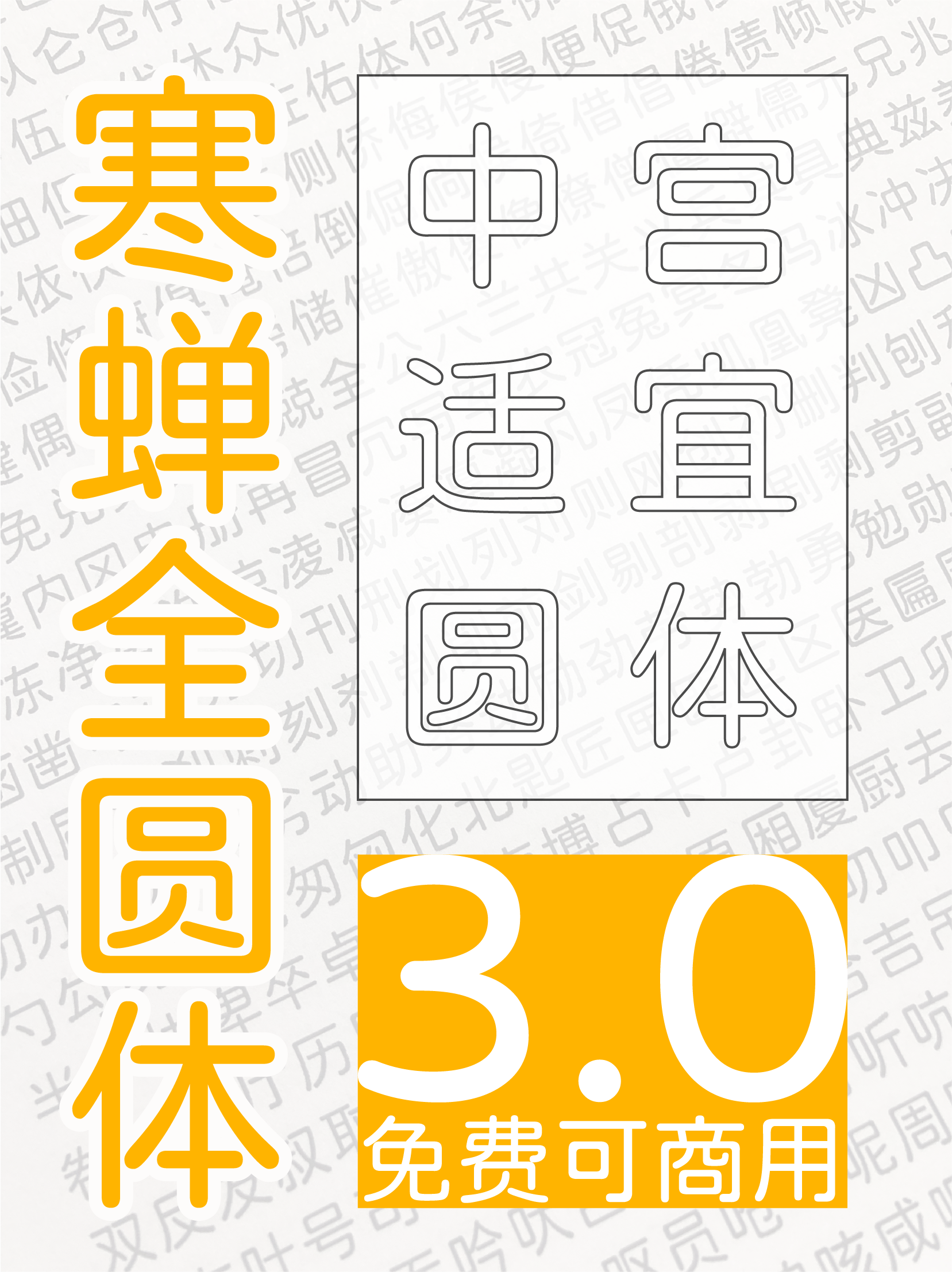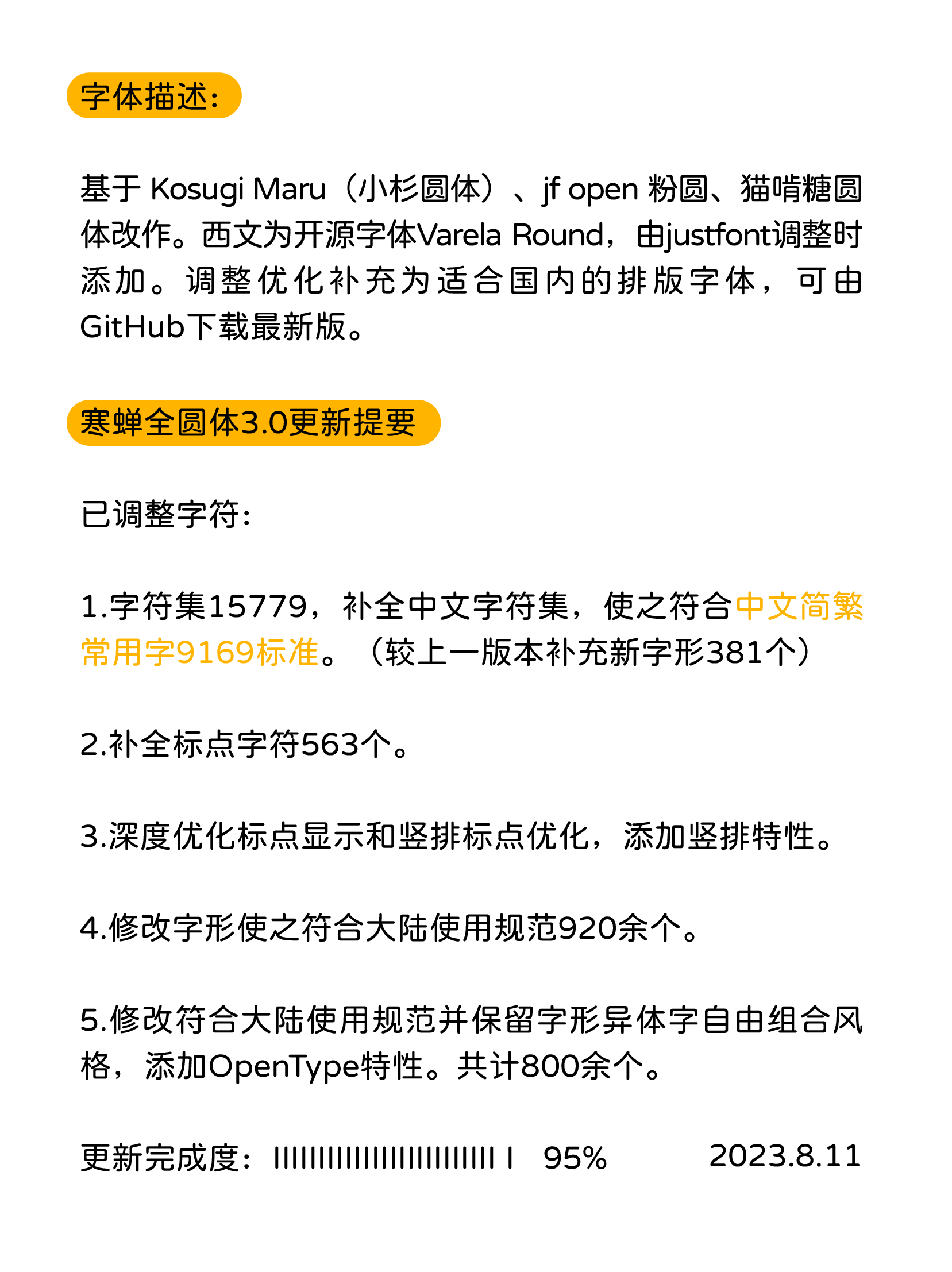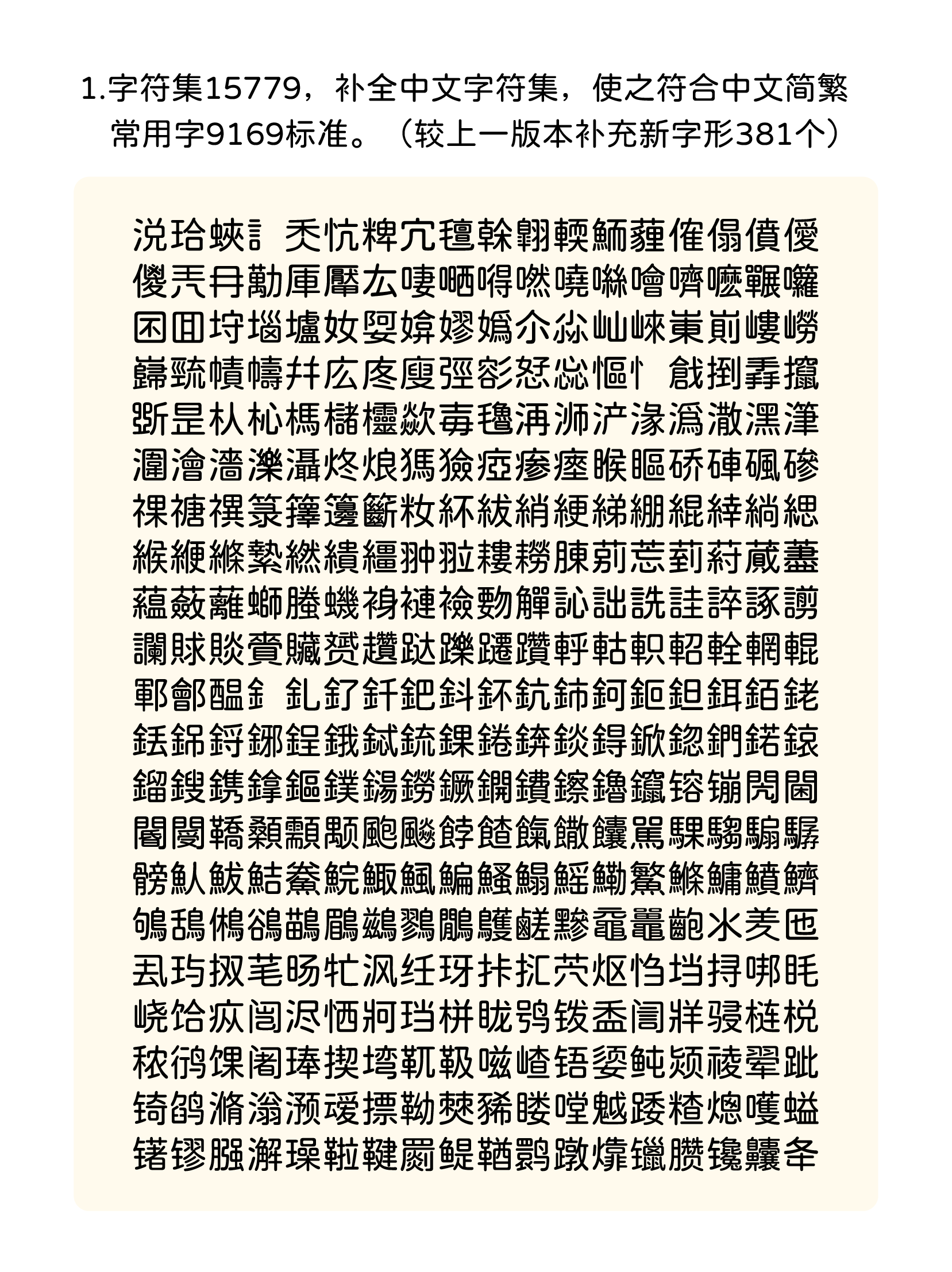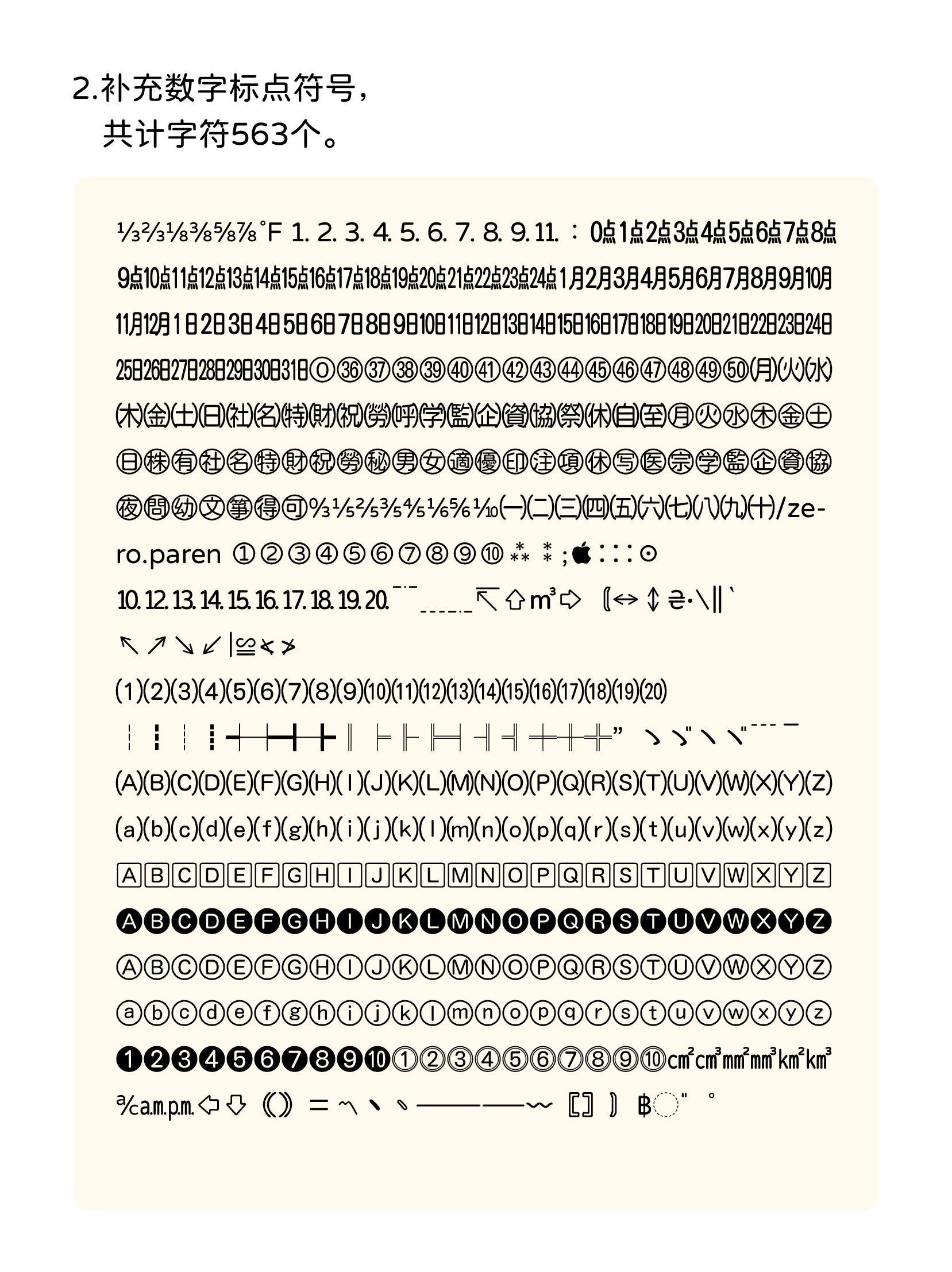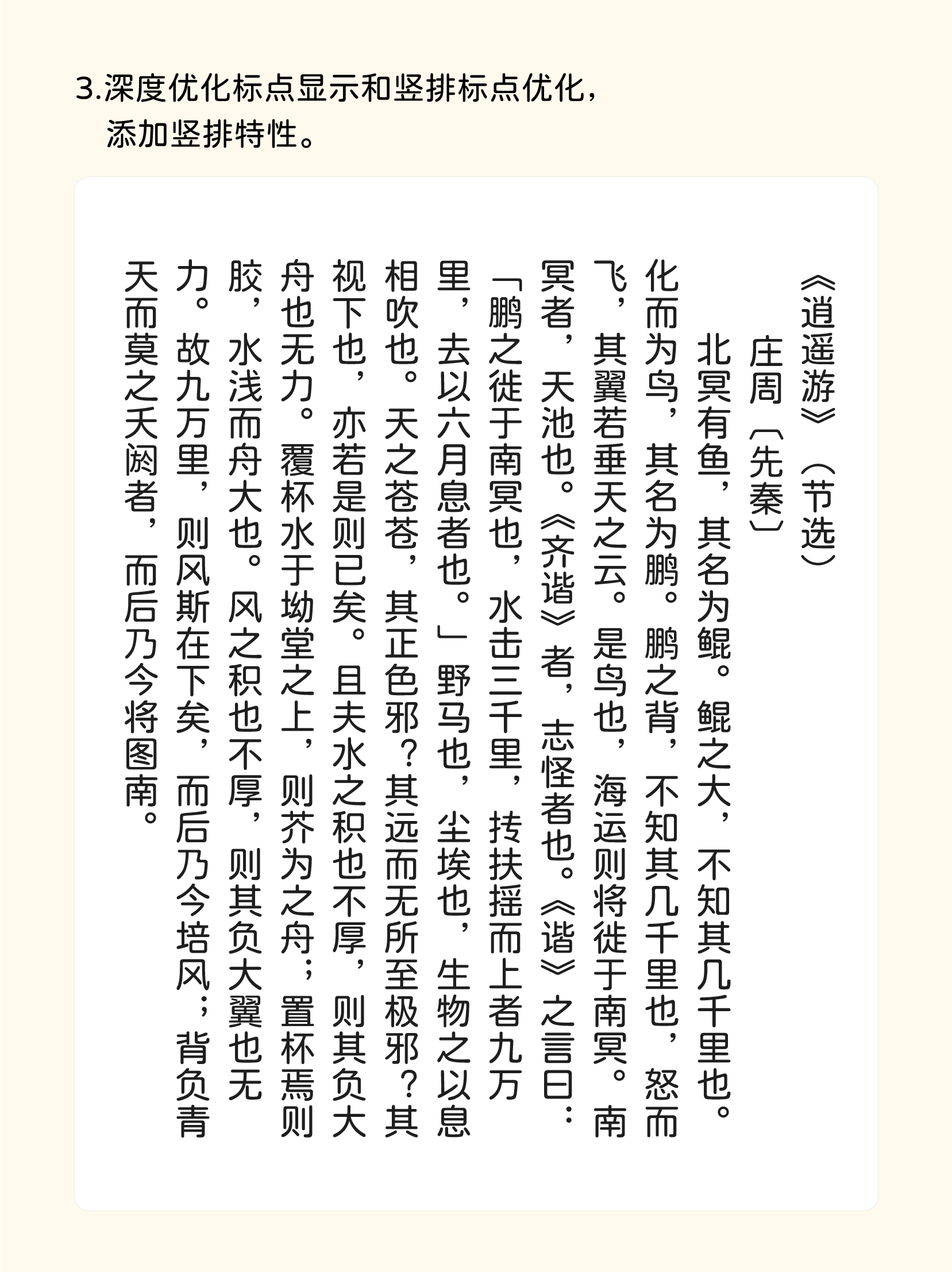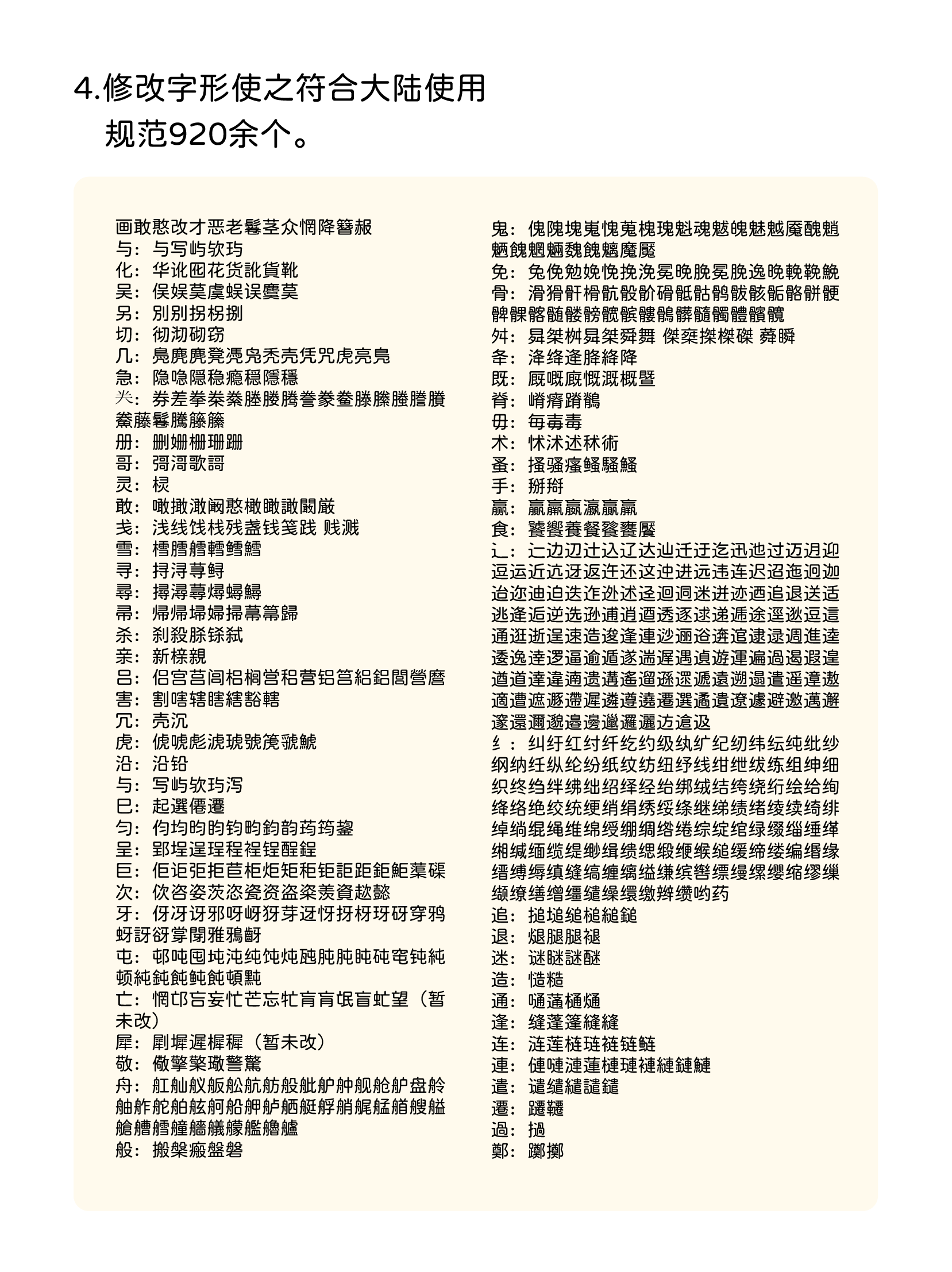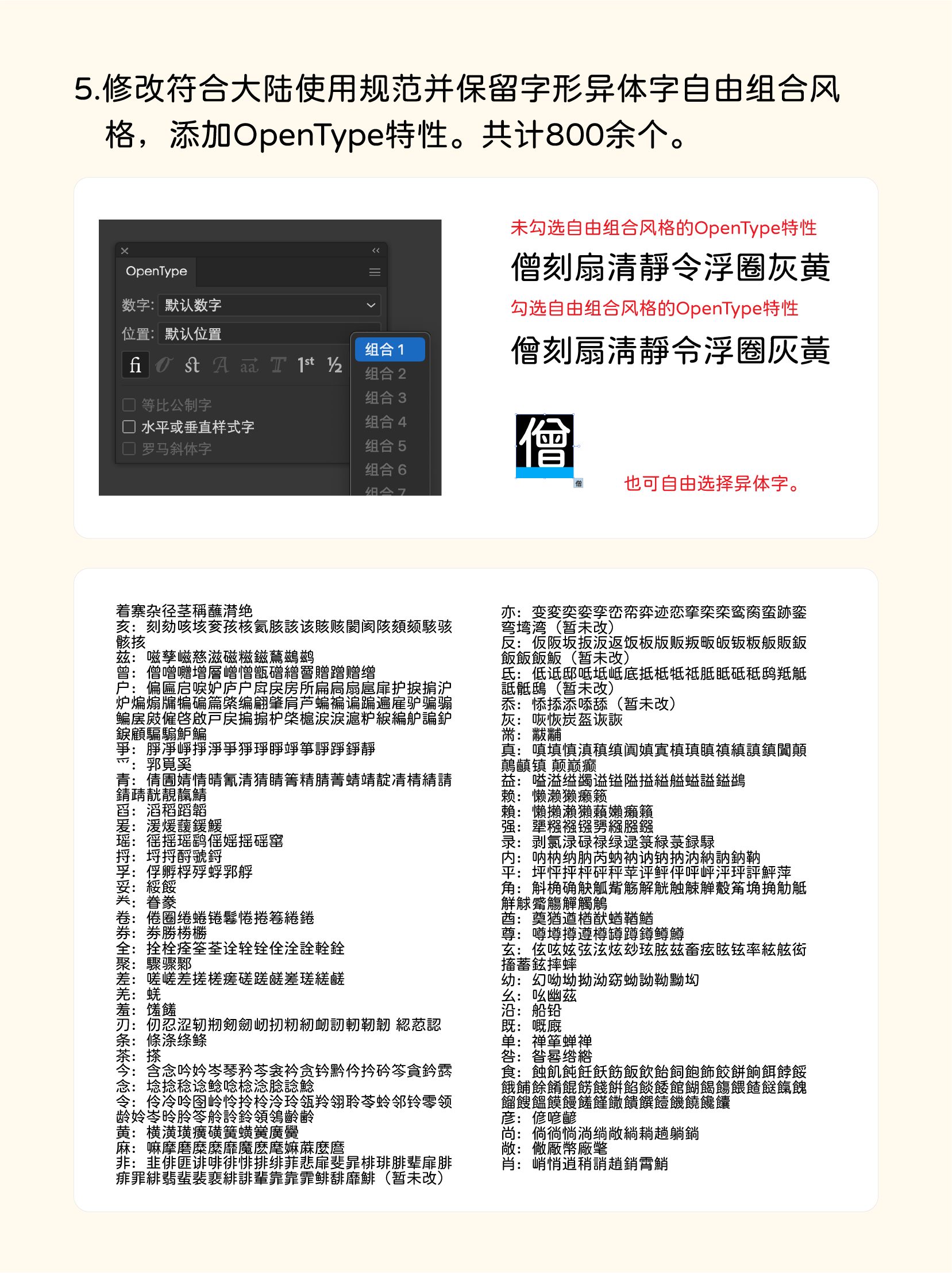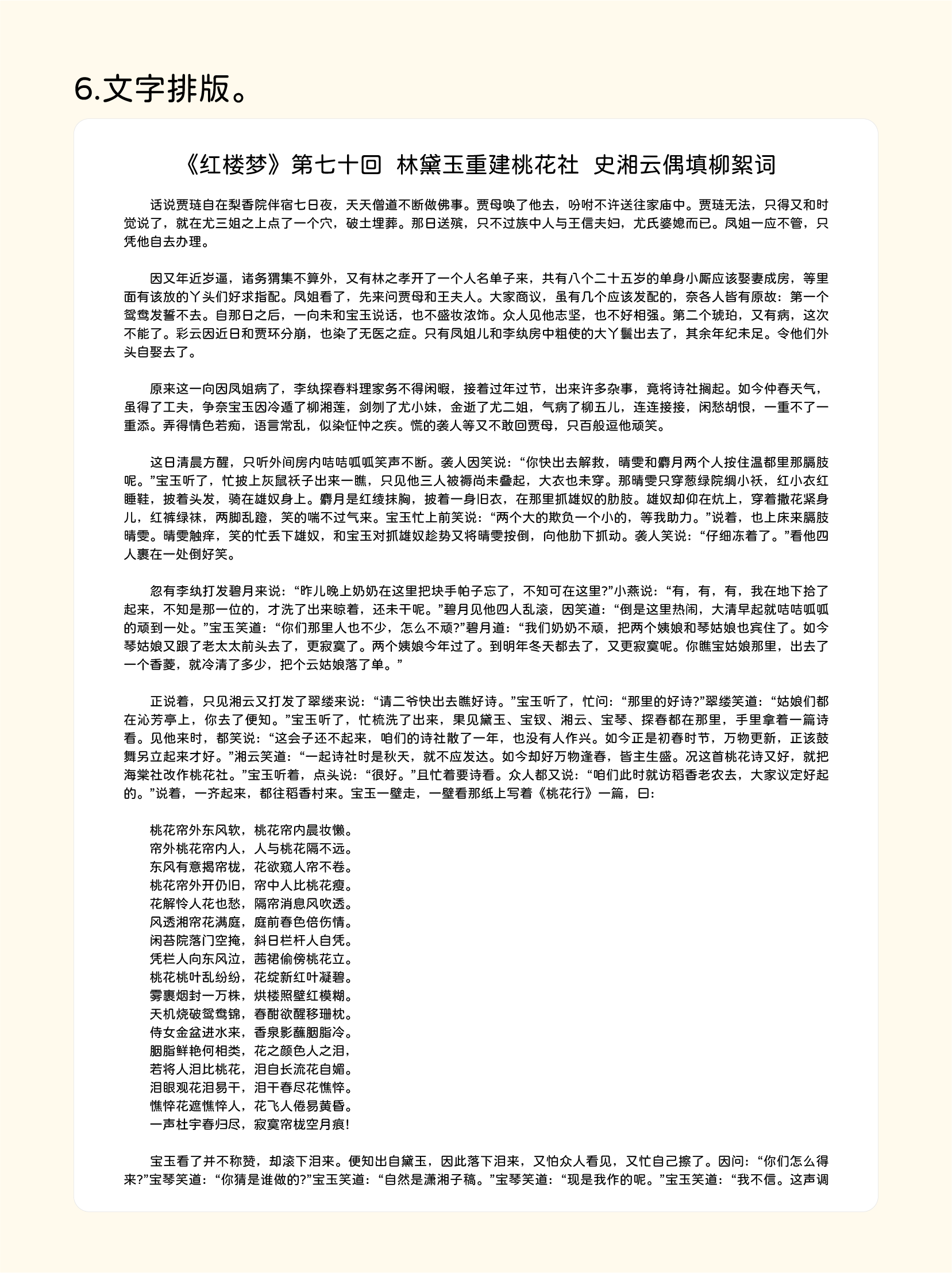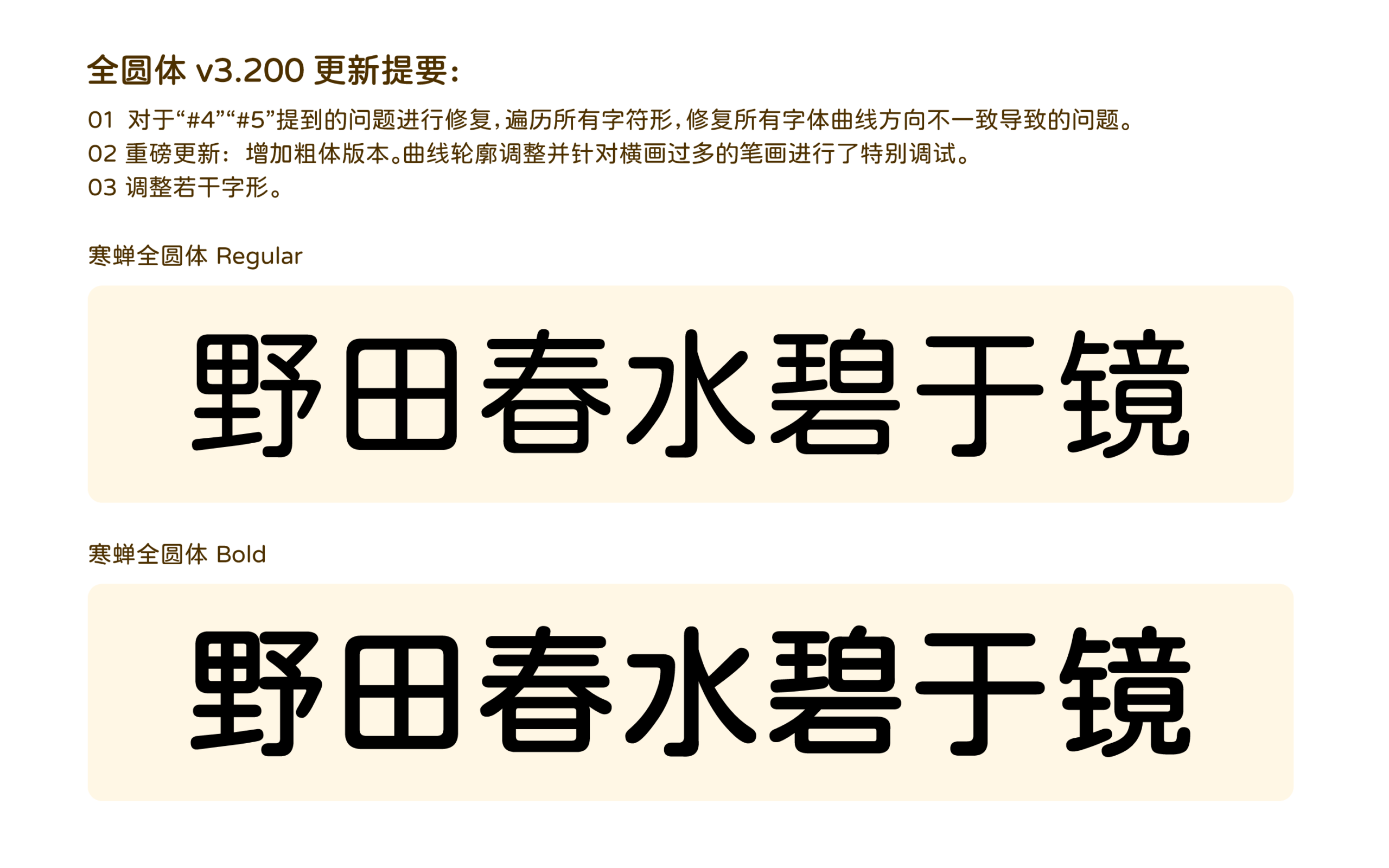
寒蝉全圆体是一款以日本开源字型“小杉圆体”(Kosugi Maru)为基础,并融合了中文开源字型“justfont粉圆”与“猫啃糖圆体”的设计特点而重新调整制作的圆体字型。此次更新的核心目标在于大幅扩展其字符集覆盖范围,将字符数量提升至超大级别,从而显著拓宽字型的实际应用场景与适用范围。 在设计与开发过程中,制作团队进行了全面的考量与细致的权衡。团队深入分析了源自不同基础字型的各版本字形,在保持整体圆润、温和视觉特征的前提下,经过反复比较与测试,从多个候选方案中筛选出最合理、最协调的字形版本作为新字型的基础。 不仅如此,本作还对字形进行了系统性的优化工作。一方面,修正了原有部分字形中存在的细节瑕疵或不协调之处,例如笔画的衔接、曲率的平滑度等;另一方面,针对原有字符集缺失或不足的部分,进行了必要的补充与绘制,以确保新字型在完整性上满足更广泛的使用需求。 最终,通过对字形结构、字重表现以及中宫松紧等多方面的综合调整,寒蝉全圆体在整体排版效果上达到了更为均衡、和谐的状态。无论是用于标题强调、界面文字还是长段落阅读,它都能提供一致、舒适且富有亲和力的视觉体验。
寒蝉全圆体3.0字体说明及更新内容:该字体基于Kosugi Maru、jf open粉圆等字体改作,西文为开源字体Varela Round;3.0版已调整字符集、补全标点、优化竖排与标点显示、修改符合大陆使用规范的字形,更新完成度95%,截至2023.8.11。
中文字符集15779中新增的381个字符展示,符合简繁常用字标准。
显示563个补充数字标点符号和字符的集合,包括各种符号、数字和字母序列。
竖排显示的《逍遥游》节选文本,演示标点优化和竖排特性效果。
展示符合中国大陆使用规范的字形修改示例列表。
OpenType设置界面显示“默认数字”选项及“组合1”下拉菜单,右侧展示启用“自由组合风格”前后“僕刻扇清静令浮圈灰黄”文本样式的对比效果,并标注可自由选择异体字“僕”。
《红楼梦》第七十回的书页,标题为“林黛玉重建桃花社 史湘云偶填柳絮词”,展示了该章节的正文内容。
全圆体 v3.200 更新提要:修复问题、增加粗体版本、调整字形,并展示 Regular 和 Bold 两种字重的效果示例。